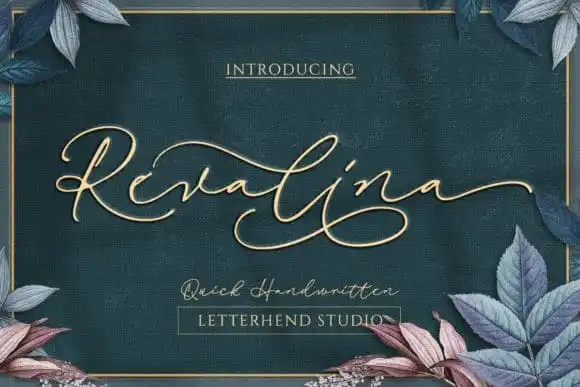
Revalina Handwritten Font – Download Grátis
Introduzimos a Revalina Handwritten Font, uma fonte elegante e com um toque natural. Desenhada e compartilhada pela Letterhend Studio, essa fonte possui um tom refinado e fluido que torna-a perfeita para coberturas de livros, headlines de revistas e muito mais. Com seu design cuidadosamente elaborado, a Revalina Handwritten Font oferece uma opção única e criativa para aqueles buscando personalidade em suas criações digitais. Suas linhas elegantes e fluidas são ideais para textos de destaque que precisam soar acolhedores e imediatistas, tornando-a perfeita tanto para aplicativos digitais quanto para projetos gráficos impressos. Seja você designer de revista, ilustrador digital ou criativo digital em geral, a Revalina Handwritten Font é uma escolha ideal. Suas formas delicadas e sua natureza fluida garantem que seu trabalho terá um toque especial e único, sem perder em elegância ou legibilidade. Experimente agora a Revalina Handwritten Font para dar um novo tom de sofisticação à sua próxima criação digital.